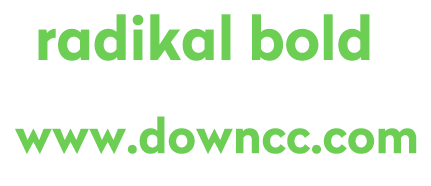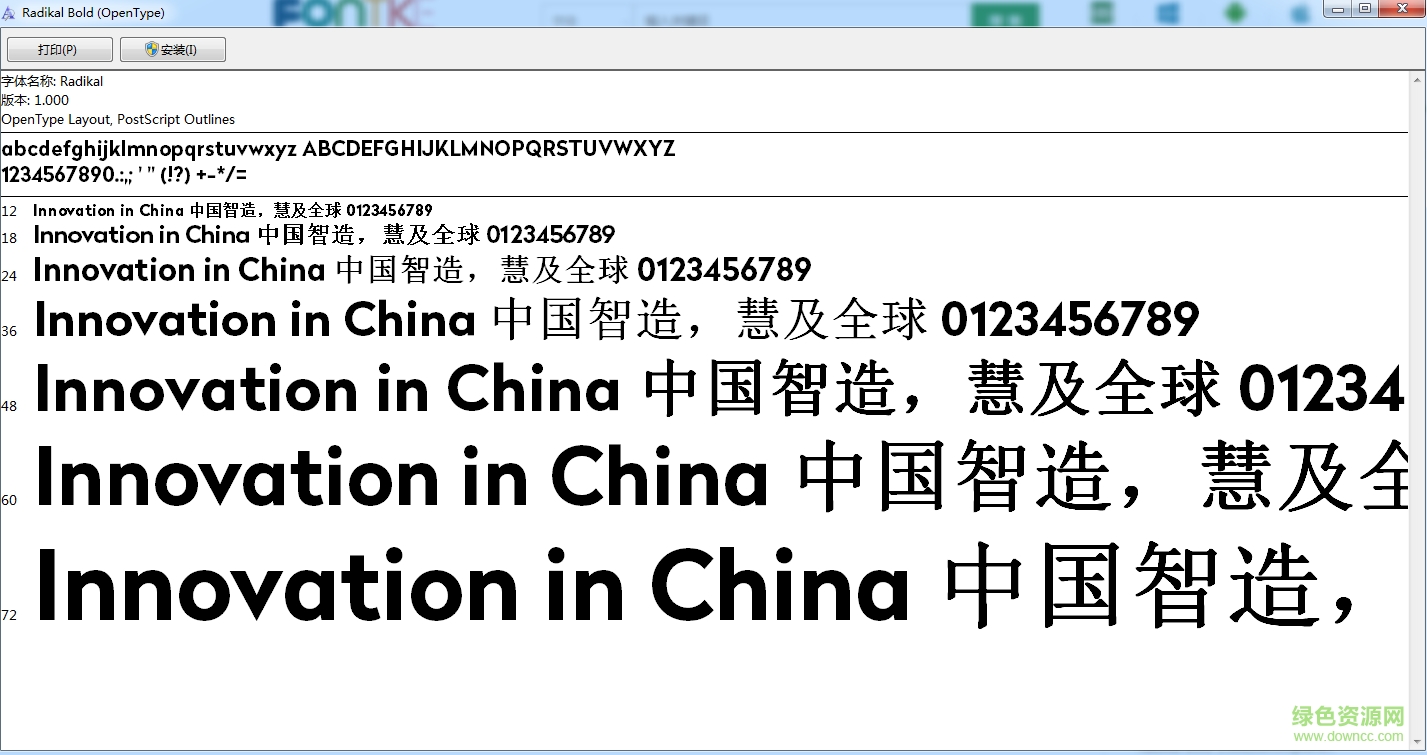
radikal bold字體是一款雅致大氣的英文無(wú)襯線字體,線條流暢,字形工整,撇捺舒展,可用在廣告設(shè)計(jì)、排版印刷或報(bào)裝設(shè)計(jì)等領(lǐng)域,需要這款字體的小伙伴趕緊來(lái)綠色資源網(wǎng)下載吧!
字體造型規(guī)整,富于力度,給人以簡(jiǎn)潔爽朗的現(xiàn)代感,有較強(qiáng)的視覺沖擊力,這種個(gè)性的字體,適合于機(jī)械科技等主題。